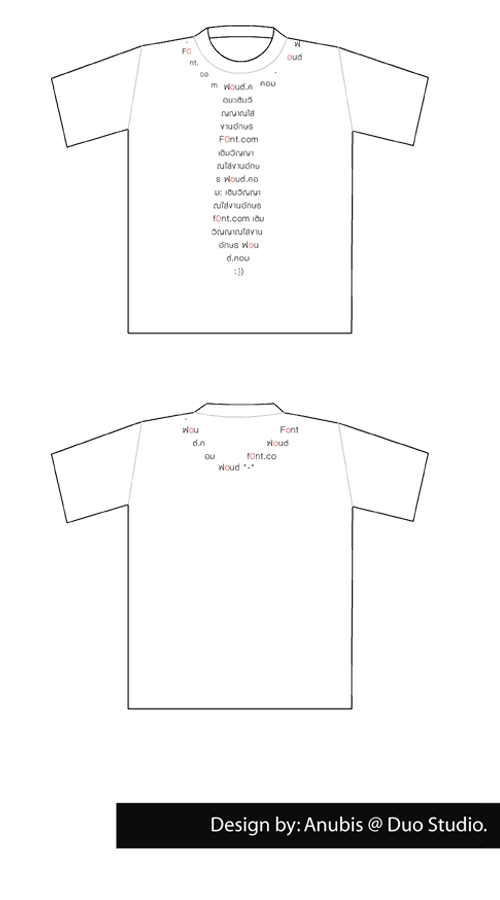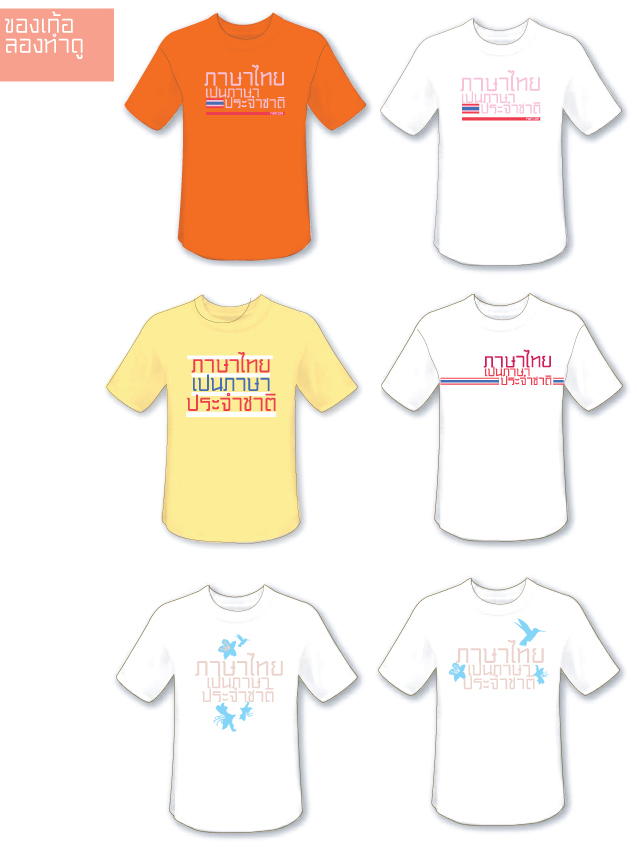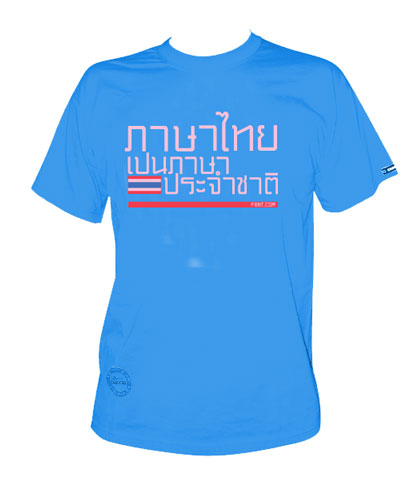
FC7 : เสื้อฟ๐นต์ ภาคสooง
ไม่เคยประกวดอะไรด้วยเลย
ลองดูบ้าง พอดีฝนตก ไปไหนไม่ได้ นั่งทำวันสุดท้ายพอดี
เอาแบบพรีเซ้นก่อน เดี๋ยวทำแบบตามกติกาแนบตามมาทีหลัง
ภาษาไทย เปนภาษาประจำชาติ
พอดีไม้ไต่คู้ดูกะกะ เอาออกซะเลย  :08:
ข้างหลังยังไม่ได้คิด แต่คงคล้ายๆคนอื่น
คือมีโลโก้เวบของพี่แอน แล้วเอาชุดสีของข้างหน้ามาแซมนิดล่ัะมั้ง
ชอบแถวที่สองขวามือ :22:
ชอบแถวสองขวามือเหมือน คนข้างบนด้วยครับ